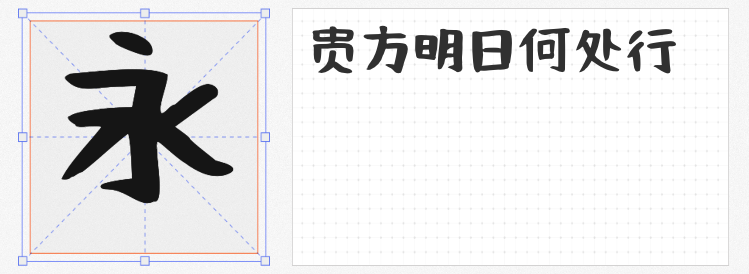
在信息过载的视觉语境中,一款兼具艺术性与辨识度的标题字体,往往能成为突破重围的视觉锚点。以下四款各具特色的字库字体,以独特的文化基因与创新技术,为设计师提供了突破常规的创意选择。
1. 阿里妈妈东方大楷
这款基于颜真卿《多宝塔碑》算法生成的字体,以机器学习复现了颜体丰腴厚重的笔墨精髓。通过智能描摹系统精准捕捉传统书法的收放韵律,既保留了落笔藏锋的古法意趣,又以规范化的骨架结构确保了现代传播的清晰度。其浑圆饱满的笔画形态,尤为适合需要传递文化厚重感的历史、教育类标题设计。
2. 阿里妈妈刀隶体
以《爨宝子碑》为灵感源泉的刀隶体,通过机器学习强化了隶书方笔的锐利特质。三角点折的几何化处理与横画"雁尾"的夸张收笔,在动静之间构建出独特的视觉张力。这种打破均衡的结构美学,既能营造出古拙质朴的历史纵深感,又可赋予科技类标题以未来主义的先锋气质。
3. 淘宝买菜营销体
这款由智能算法生成的个性化字体,以6974个汉字的完整字符库构建起强大的实用基础。通过深度学习技术赋予笔画独特的肌理质感,在保持视觉统一性的同时,为不同场景提供多样化的风格演绎。其模块化设计思维显著提升设计效率,尤其适合需要快速迭代的电商营销场景。
4. 可爱手写体
突破毛笔字体可读性局限的这款手写体,以"视认性优先"为设计原则,在保留书写自然韵律的同时优化了笔画清晰度。介于楷书与行书之间的灵动结构,既适合年轻化品牌的标题设计,也能为传统促销物料注入清新活力,实现文化基因与现代审美的平衡。
当技术赋能遇见文化传承,这四款字体以不同的创新路径拓展了标题设计的可能性。它们不仅是视觉表达的载体,更是连接传统美学与数字时代的创意桥梁,为设计师解锁了突破同质化竞争的视觉密码。